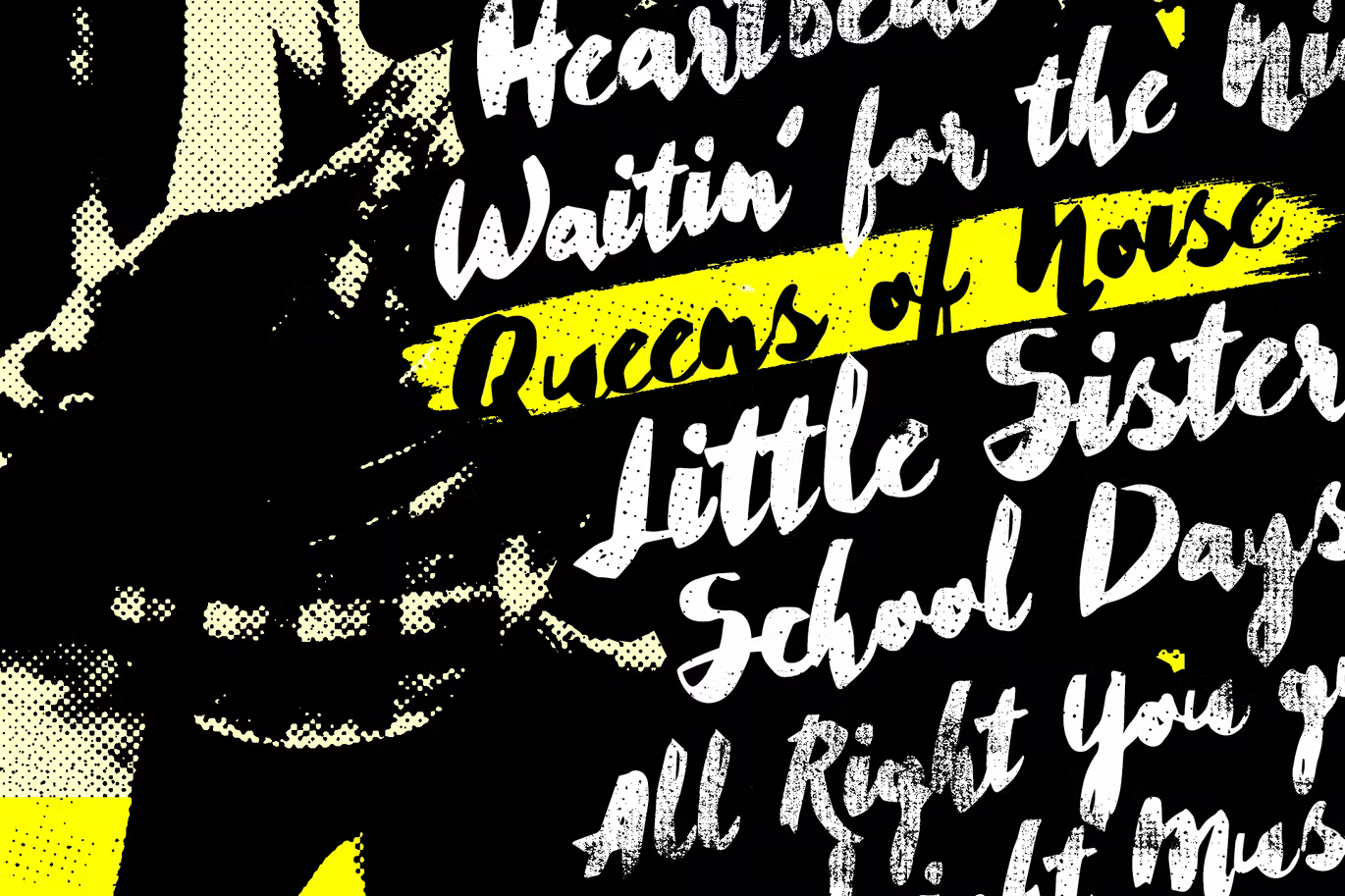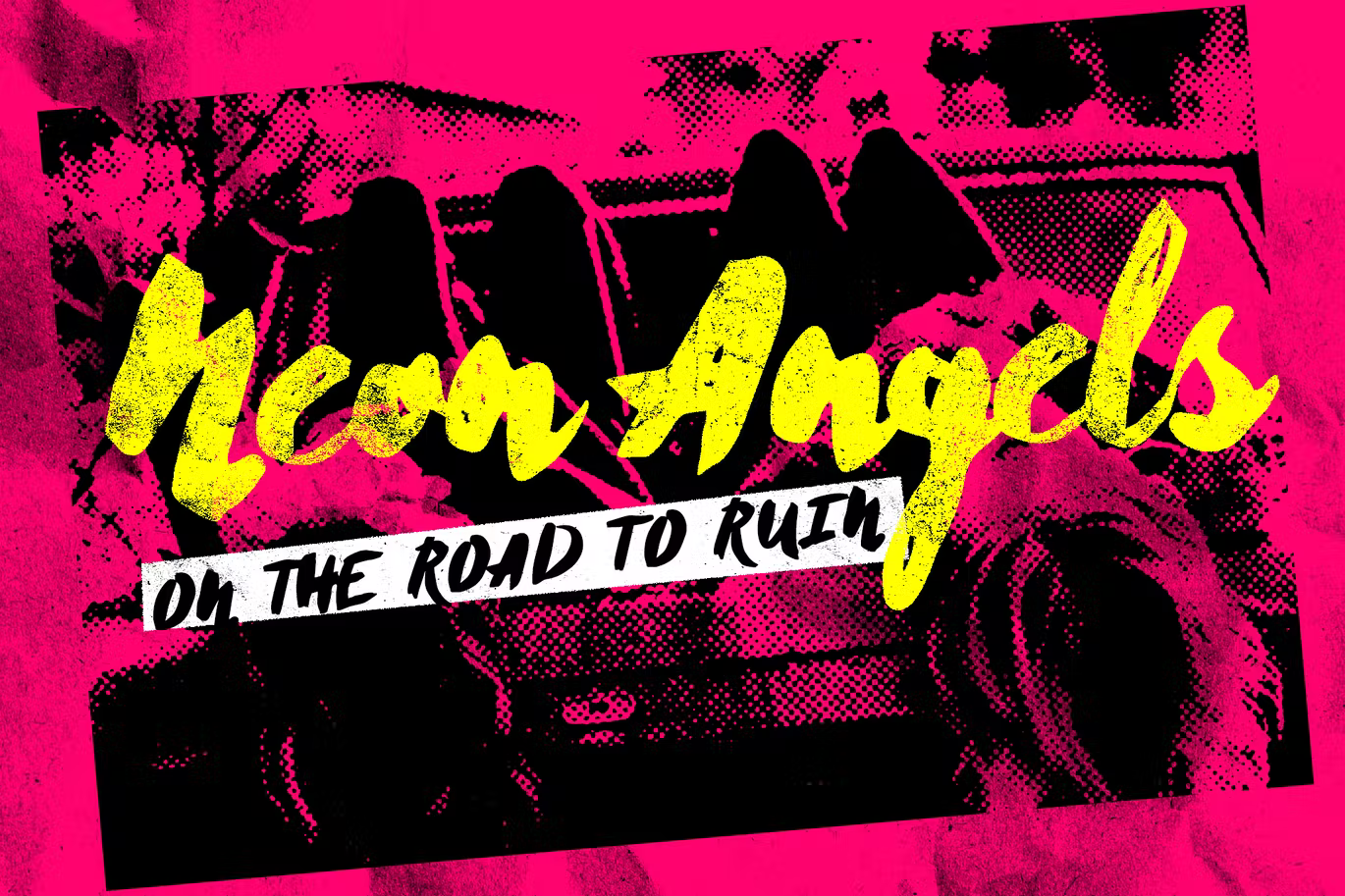
Cherie Bomb Font
Description de Cherie Bomb Font
Cherie Bomb est une police de pinceau faite à la main avec un sentiment punk-rock, mais avec de la personnalité et du cœur. Il vous permettra de créer de superbes lettrages manuscrits rapidement et facilement.
Cherie Bomb comprend plus de 350 caractères, majuscules et minuscules, des signes de ponctuation de base, des chiffres et fonctionne très bien avec de nombreuses langues internationales en plus de l’anglais.